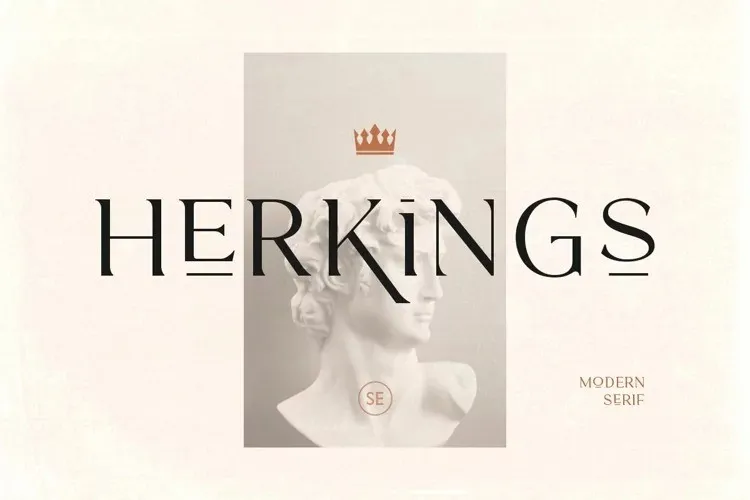
Esta fonte serif chamada Herkings foi projetada por Saridezra com um estilo minimalista que oferece elegância clássica ao mesmo tempo que incorpora características modernas. Ela é perfeita para aplicação no logotipo e também funciona bem como parte de uma identidade visual de marca, tornando-a versátil e adaptável a diversos usos. O designer sugeriu que você misture letras maiúsculas e minúsculas na criação do seu logo para um resultado mais único e destacado. Além disso, esta fonte é altamente compatível com múltiplos idiomas, dando-lhe uma ampla gama de possibilidades criativas. Seja você um designer profissional ou um iniciante no design gráfico, a Herkings pode trazer profundidade ao seu trabalho, seja para criar uma identidade visual memorável ou simplesmente dar um toque sofisticado em qualquer projeto de texto.